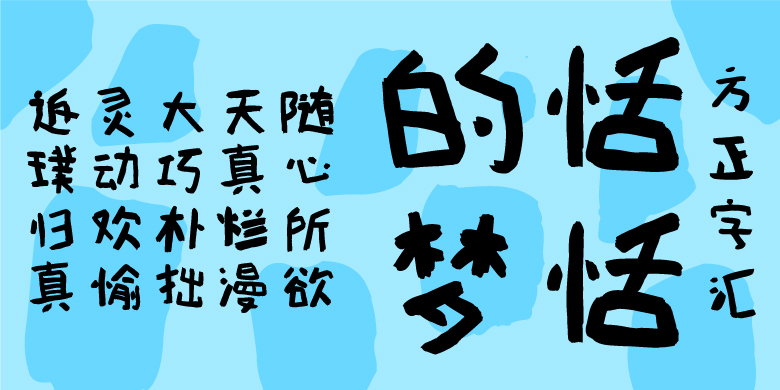
方正字汇-恬恬的梦
字体品牌: 方正字汇 设计师:李佛君 字体分类:创意书写 字体属性:精品字 字符集:大陆简体(GB2312-80) 发布时间: 2023
字体创意灵感来源于作者女儿(恬恬)三岁时的日常涂鸦,字形随心所欲,天真烂漫,大巧朴拙,灵动欢愉。成年人常常追寻的返璞归真,在孩童来看,信手拈来,作者希望这样满怀初心的字样可以走入寻常的视野,呼唤人们回归朴素,重拾至纯至精、至简至美之心。